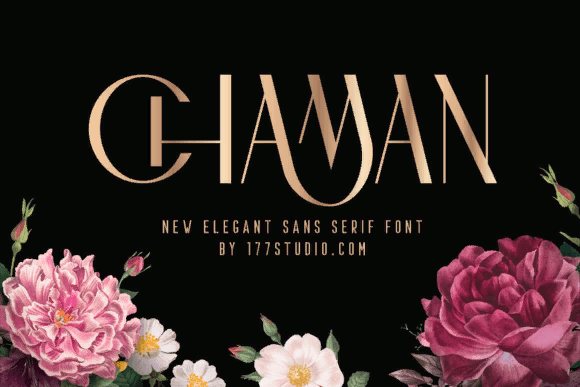
Название: Chaman Elegant Font
Chaman - элегантный и совреме
Влюбитесь в его невероятно универсальный стиль и используйте его для создания эффектных дизайнов!